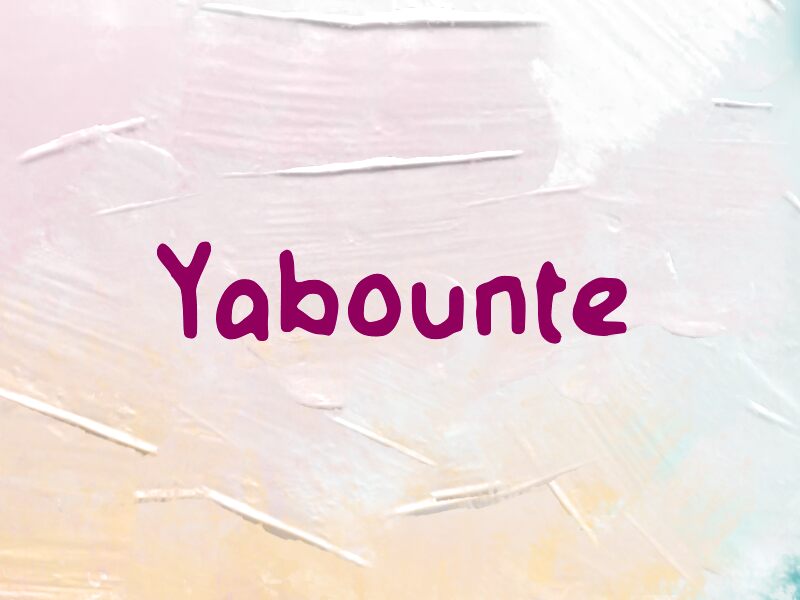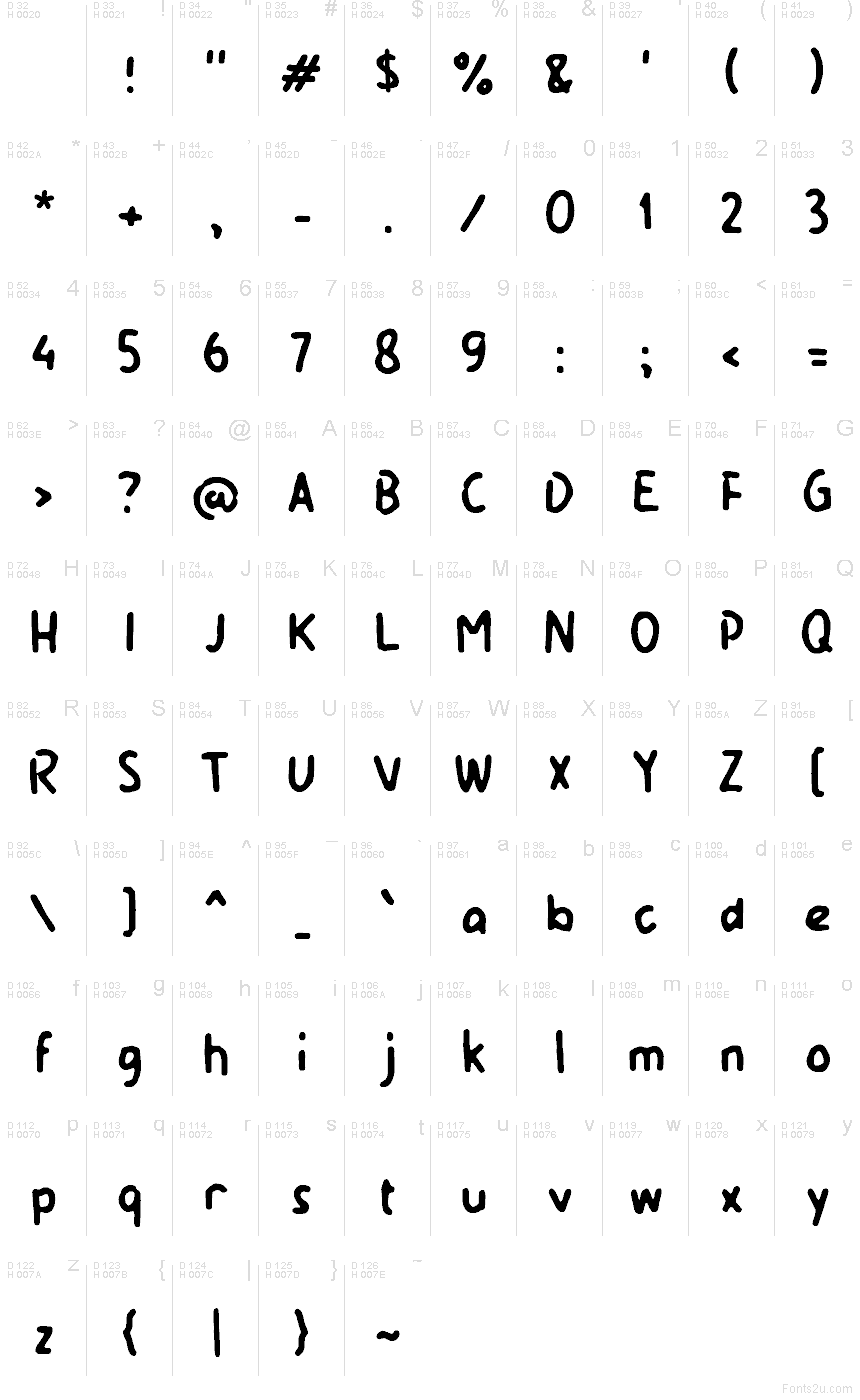
Yabounte от Wep — это бесплатный «толстенький» шрифт-кисть с игривым рукописным настроением. Буквы выглядят мягкими и объемными: закругленные концы, динамичные изгибы и легкий неравномерный ритм подчеркивают живой характер мазка, не давая шрифту стать слишком прилизанным.
Он отлично впишется в молодежный брендинг, меню кафе, заголовки плакатов, упаковку и титульные карточки для соцсетей, где дружелюбный рисованный стиль выглядит естественнее, чем выверенные каллиграфические шрифты. Поскольку Yabounte распространяется бесплатно, он также хорош для коротких надписей и быстрых эскизов логотипов, ведь широкие, «пухлые» штрихи придают даже коротким словам теплую, домашнюю атмосферу.
Yabounte
Презентация и наглядный образец шрифта Yabounte